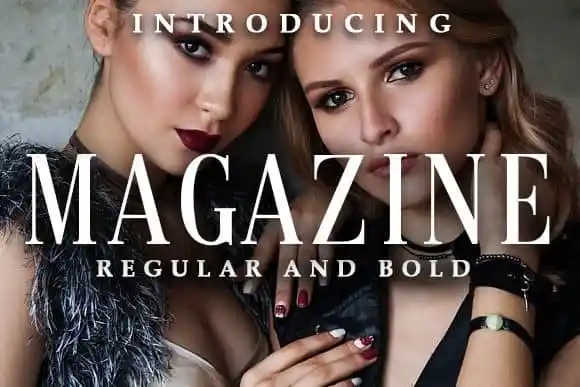
Magazine Serif Font é uma fonte serif com pés fortes e moderna, cuidadosamente criada pelo designer Vladimir Nikolic. Este recurso gráfico foi desenvolvido para complementar projetos que exigem elegância e profundidade, permitindo aos designers criar designs de capa, headlines, cartazes, logotipos, selos, camisetas e muito mais. Ideal tanto para aplicativos como letras em postagens, logotipos, cartazes, certificados e selos. Com suas linhas redondas e detalhes cuidadosamente construídos, Magazine Serif é uma escolha perfeita para quem busca qualidade sem comprometer a estética e a consistência visual de um projeto.